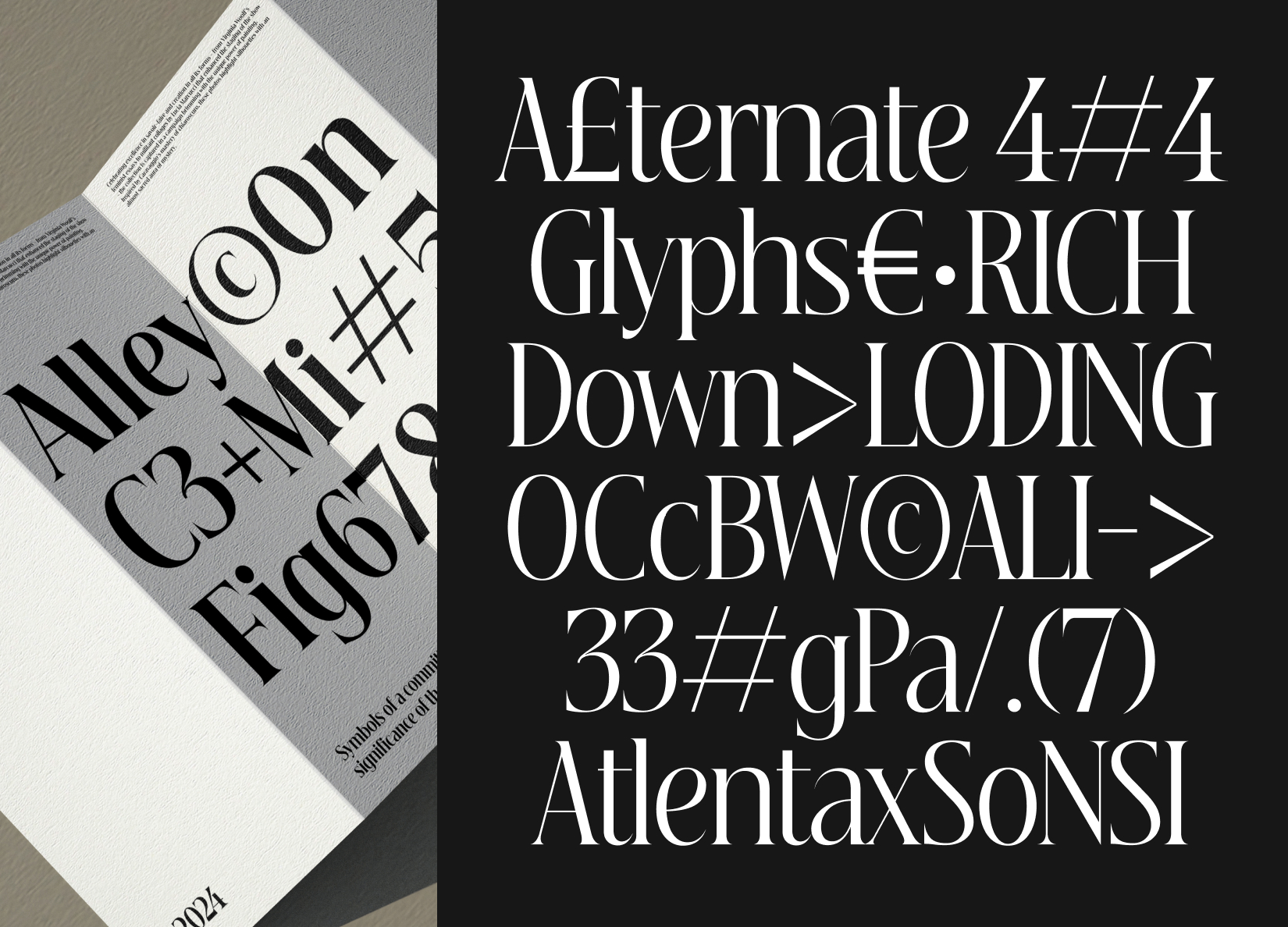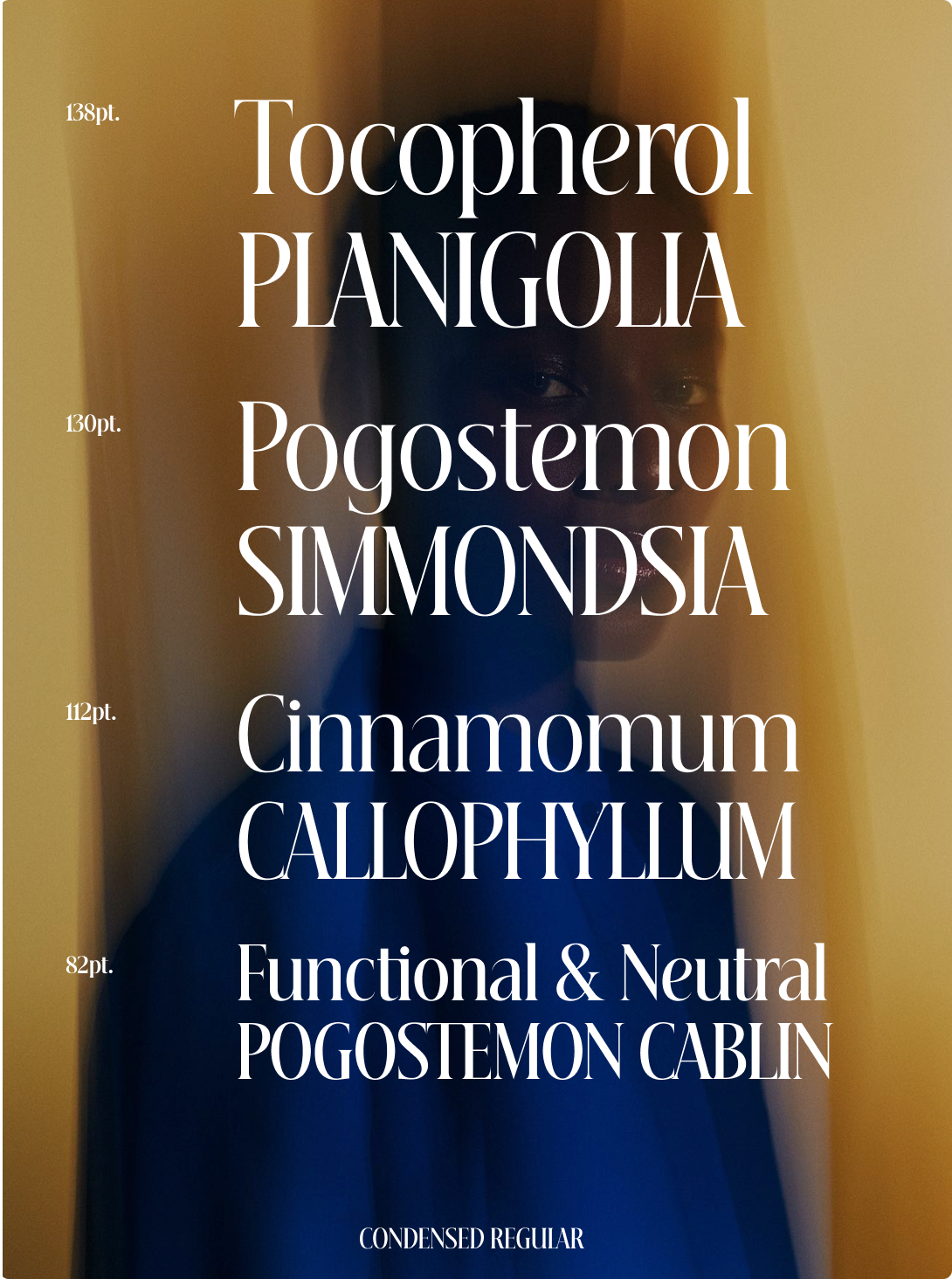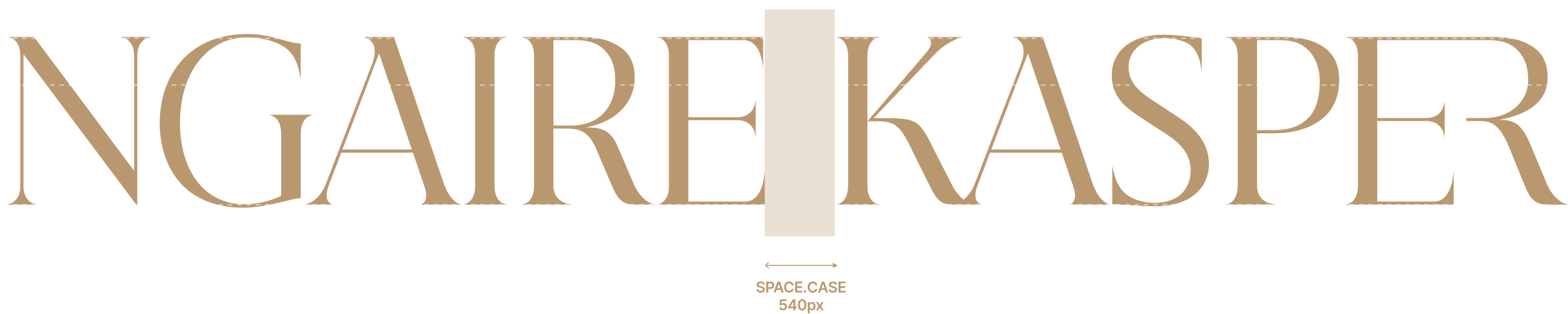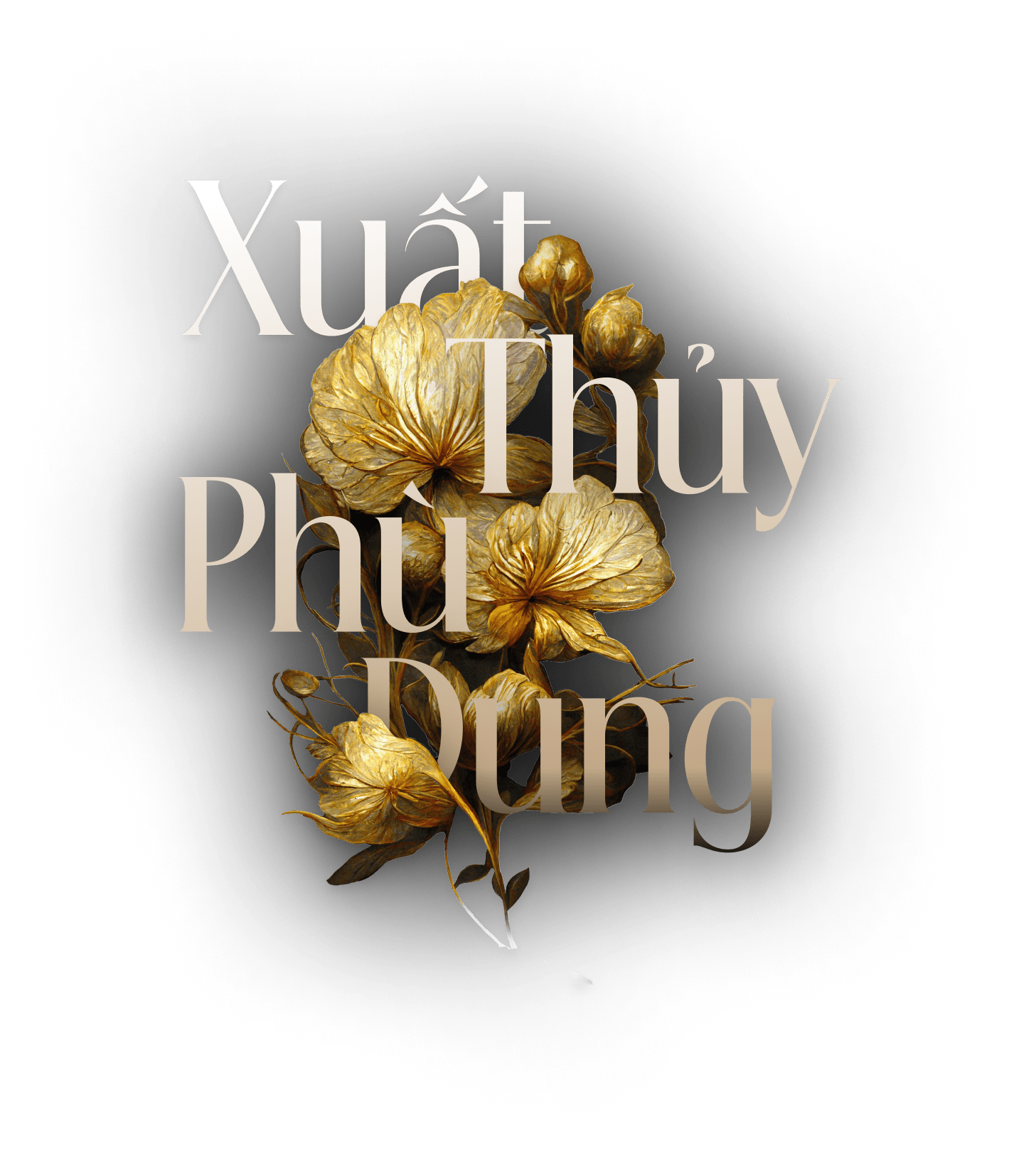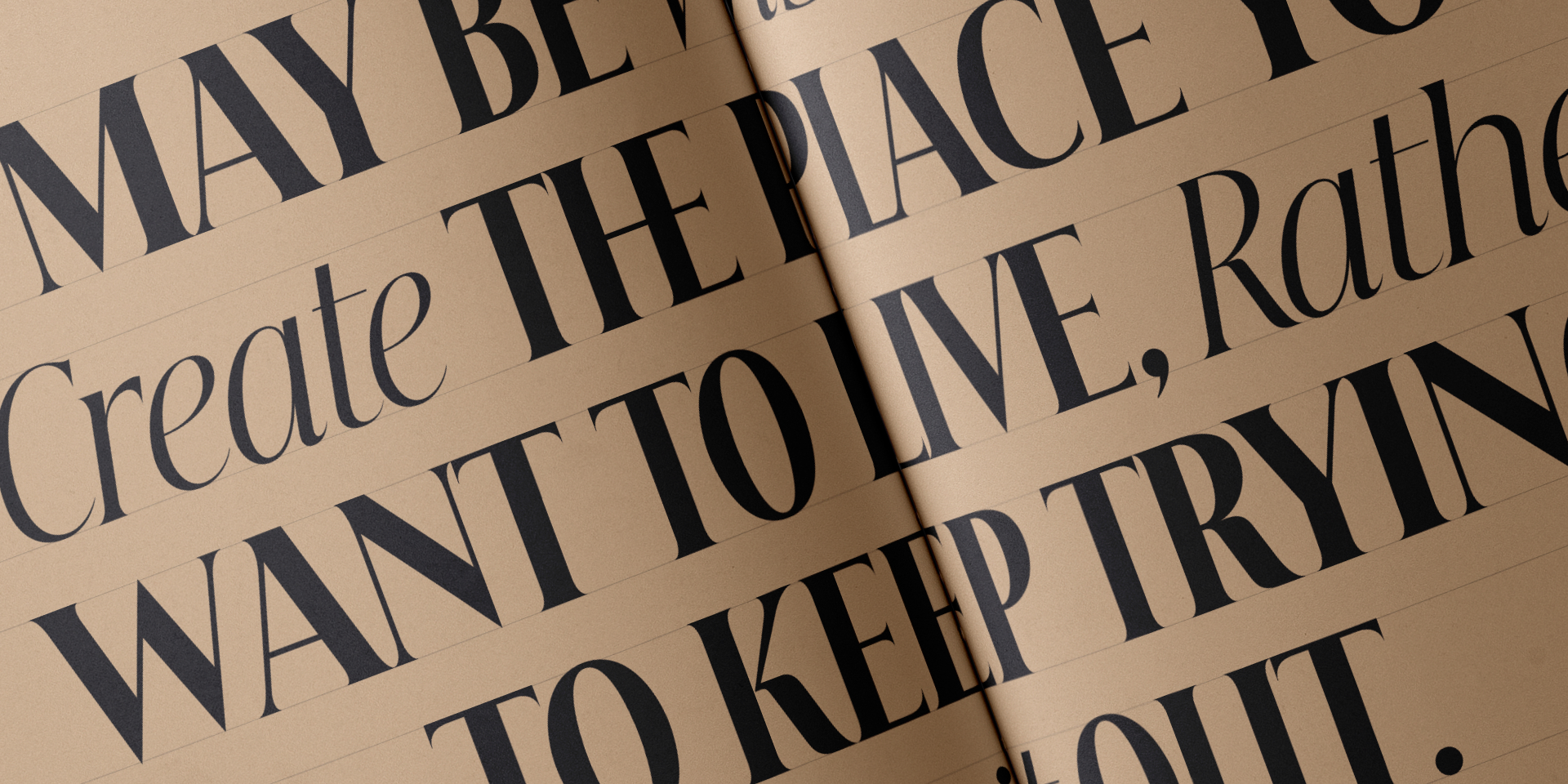
Ẩn dụ của
lý luận và sắc thái
biểu cảm
Beautique Display là bộ typeface độc quyền được
phát triển bởi team BeauType Studio
Beautique là phân nhánh chuyên về phát triển chiến lược và trải nghiệm thương hiệu của Beau Agency. Với kinh nghiệm lâu năm của mình, chúng tôi hiểu rằng: Typeface là mảnh ghép còn thiếu cuối cùng để hoàn thiện về trải nghiệm của một thương hiệu. Đây là lĩnh vực mà không phải đơn vị trong nước nào cũng có năng lực triển khai. Chính vì thế, BeauType Studio càng phải là người tiên phong
Đa dạng weight and style chữ
Cơ sở lý luận
Mục đích của BeauType Studio khi phát triển bộ font này là để ứng dụng trên các nền tảng số và ấn phẩm của Beautique.
Là một đơn vị đề cao yếu tố nghệ thuật trong các sản phẩm sáng tạo, chúng tôi quyết định sử dụng những tư duy cốt lõi trong nền móng của Calligraphy cổ điển, đặc biệt là hệ thống bảng chữ cái La Mã. Trong đó, từng con chữ đều được cân nhắc kỹ càng về tỷ lệ và đường nét
Yếu tố đồng nhất
Để hình thành được một bộ typeface hoàn chỉnh, từng chi tiết bên trong phải được xây dựng một cách khoa học và hệ thống. Trong đó, các thành tố căn bản đều được ứng dụng đồng nhất trong thiết kế của từng chữ cái. Phần dấu cho các ký tự tiếng Việt được căn chỉnh theo hệ thống điểm neo
Typeface đa dạng weight và kích cỡ, được thiết kế tinh tế và tính toán kỹ lưỡng để tạo ra hiển thị ấn tượng ở kích cỡ lớn.
Beautique Display Sans có hai dạng: Chữ thẳng và chữ nghiêng
Typeface được thiết kế với mục đích “bản địa hóa” chữ serif cổ điển, nêu bật lên tính cách thương hiệu Beautique, đồng thời hiển thị tối ưu các trường hợp sử dụng dấu tiếng Việt.
Beautique Display Sans chứa đủ tất cả dấu và ký tự tiếng Việt/ tiếng Pháp
Typeface chứa đựng tới 23 ký tự liên hợp được thiết lập từ các cặp chữ kép có quan hệ thống nhất với nhau bằng những bộ phận vốn tương đối độc lập
beautique display version 1.1
Beautique Display - Phiên bản mới mang đến trải nghiệm thiết kế hoàn hảo hơnBeautique Display, typeface serif hiện đại và thanh lịch, tự hào ra mắt phiên bản mới 1.1 với những cải tiến vượt trội, mang đến cho người dùng trải nghiệm thiết kế hoàn hảo hơn bao giờ hết. Phiên bản mới này là kết quả của quá trình nghiên cứu và trau chuốt tỉ mỉ, nhằm đáp ứng nhu cầu ngày càng cao của các nhà thiết kế chuyên nghiệp.
01Điều chỉnh lại tỉ lệ một số
ký tự cho hợp lý
Version 1.0
Version 1.1
02Điều chỉnh lại spacing,
gia tăng số cặp kerning
03Bổ sung các trường hợp
case-sensitive trong
OpenType
case-sensitive off
case-sensitive on
04Thích ứng kích thước khoảng space để
văn bản All Caps trở nên dễ đọc hơn
04Thích ứng kích thước
khoảng space để văn bản
All Caps trở nên dễ đọc hơn
05Bổ sung đầy đủ hệ thống
Ligature cho bộ chữ Italic
Ligature set
- AA
- EA
- ER
- ET
- FL
- FT
- LA
- NN
- TE
- TT
- TV
- TW
- YT
- HE
- TY
- Th
- ch
- fi
- fl
- ft
- ti
- tt
- tu
- tr